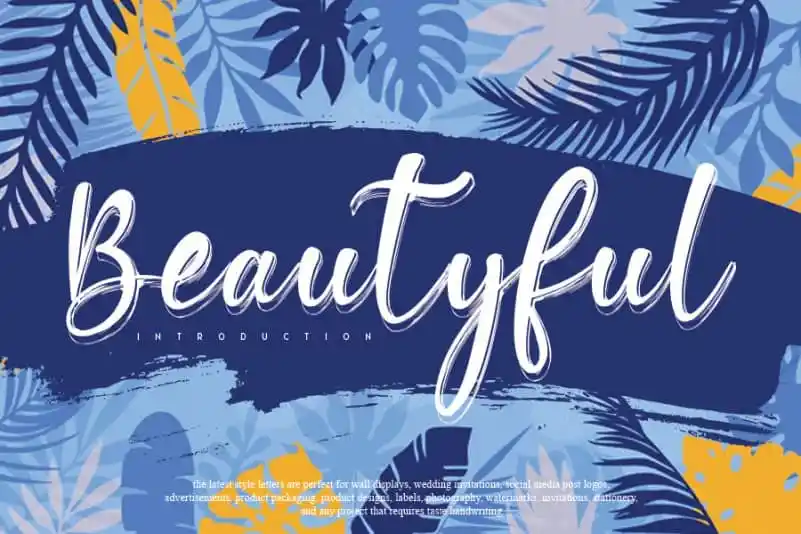
A Beautyful Script Font oferece a elegância sofisticada simplificada numa única fonte script de altíssima qualidade. Desenvolvida pelo designer andikastudio, essa fonte mantém influências clássicas do calligrafismo enquanto permanece atual e fresca no seu design. Suas características versáteis a tornam apropriada para uma ampla gama de ideias criativas, adequadas tanto para as cartões de endereço quanto aos títulos, bem como ao design de materiais de escritório. Seja você um designer gráfico ou alguém que busca adicionar um toque sofisticado e único aos seus trabalhos manuscritos, a Beautyful Script Font é uma opção perfeita para suas necessidades.